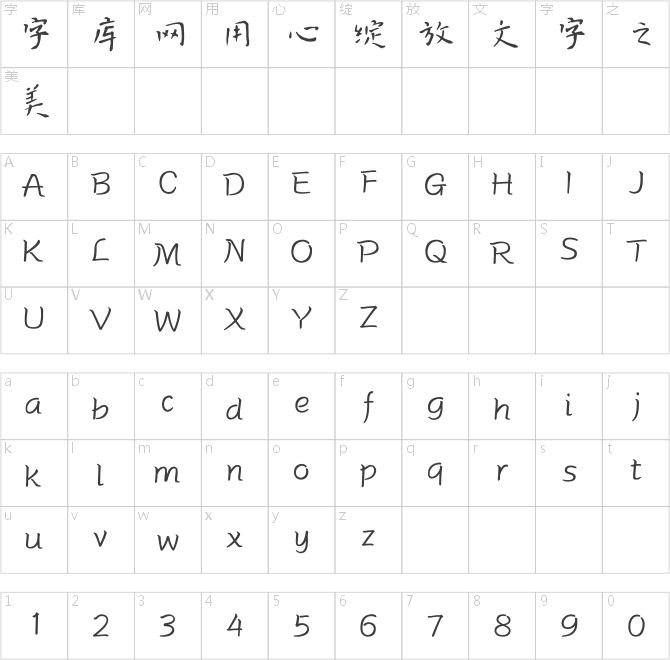
方正字跡-毛海飛古典楷書
今日生活之匆忙,靈魂跟不上生活節奏。追求內心質樸自然,平和,結構厚重而不浮,質樸而不板,深沉而不狂,點畫不雕鑿,不裝巧,一任舒服渾然天成的感覺。
方正字跡-毛海飛古典楷書字體FZZJ-MaoHFGDKSJF簡繁版字庫是一款讓人賞心悅目、百看不厭的中文字體,適合各類廣告和產品包裝設計應用,字體大小7.37MB,格式為TTF字體,上傳用戶是我,Dirac,作者/版權方為方正字庫